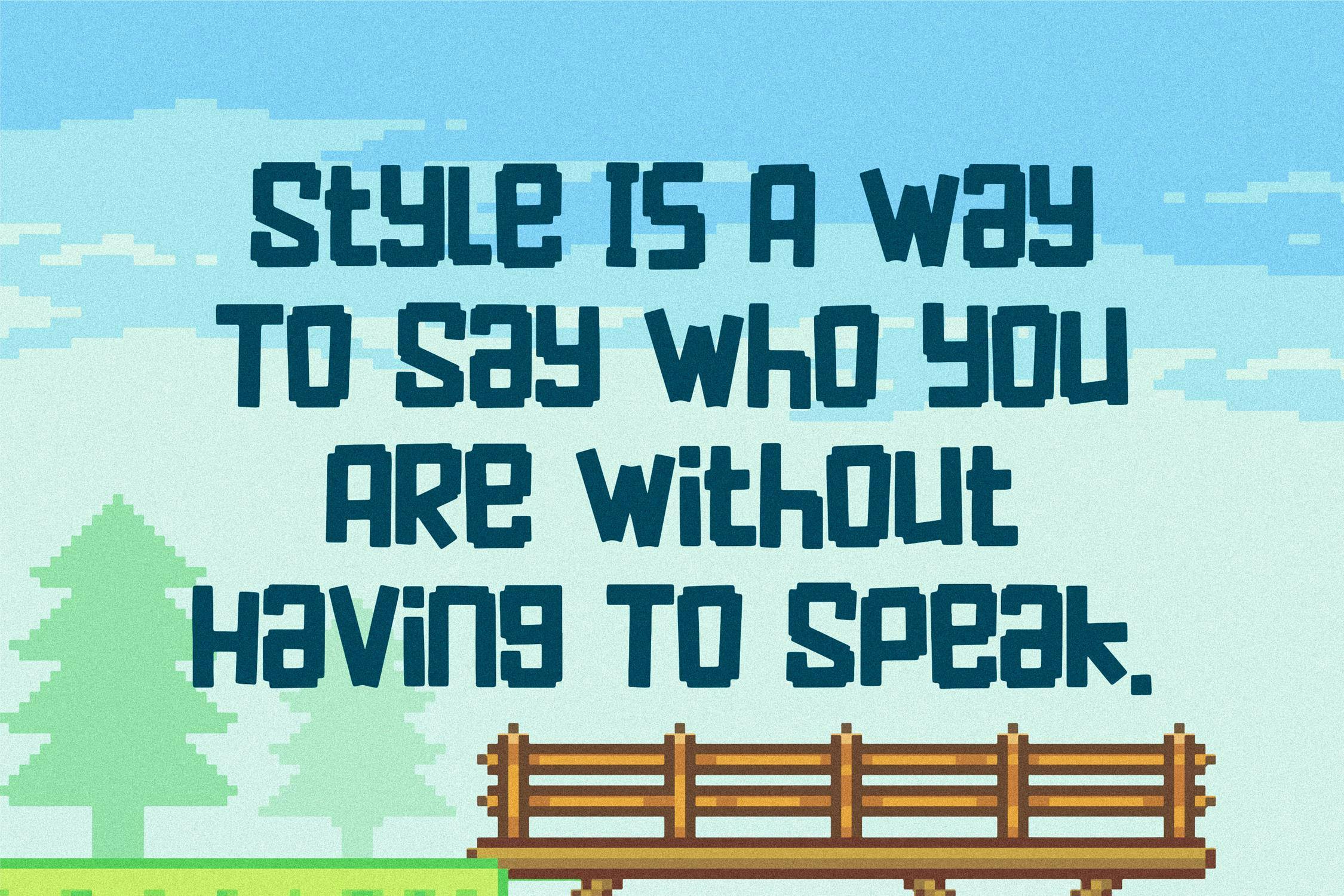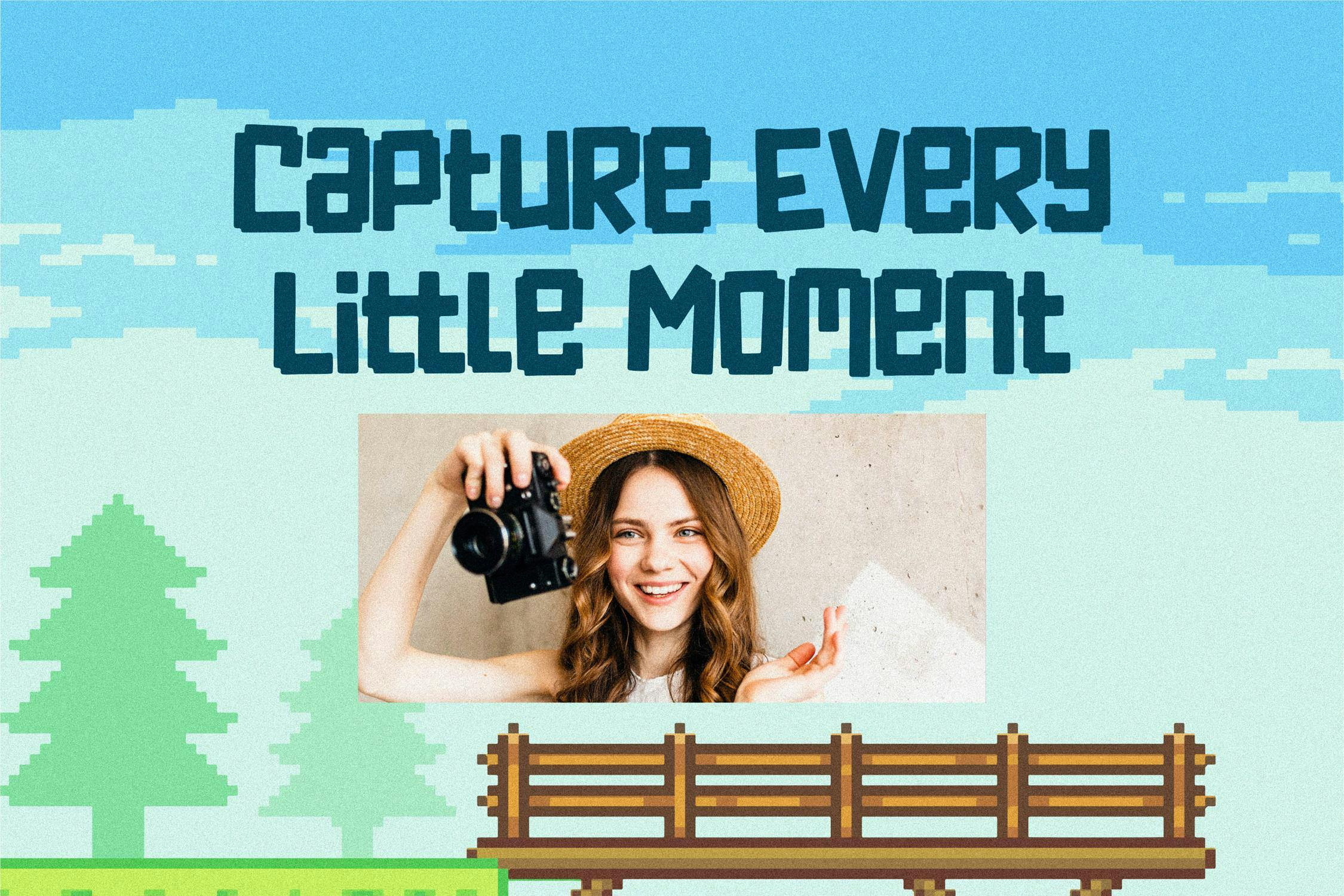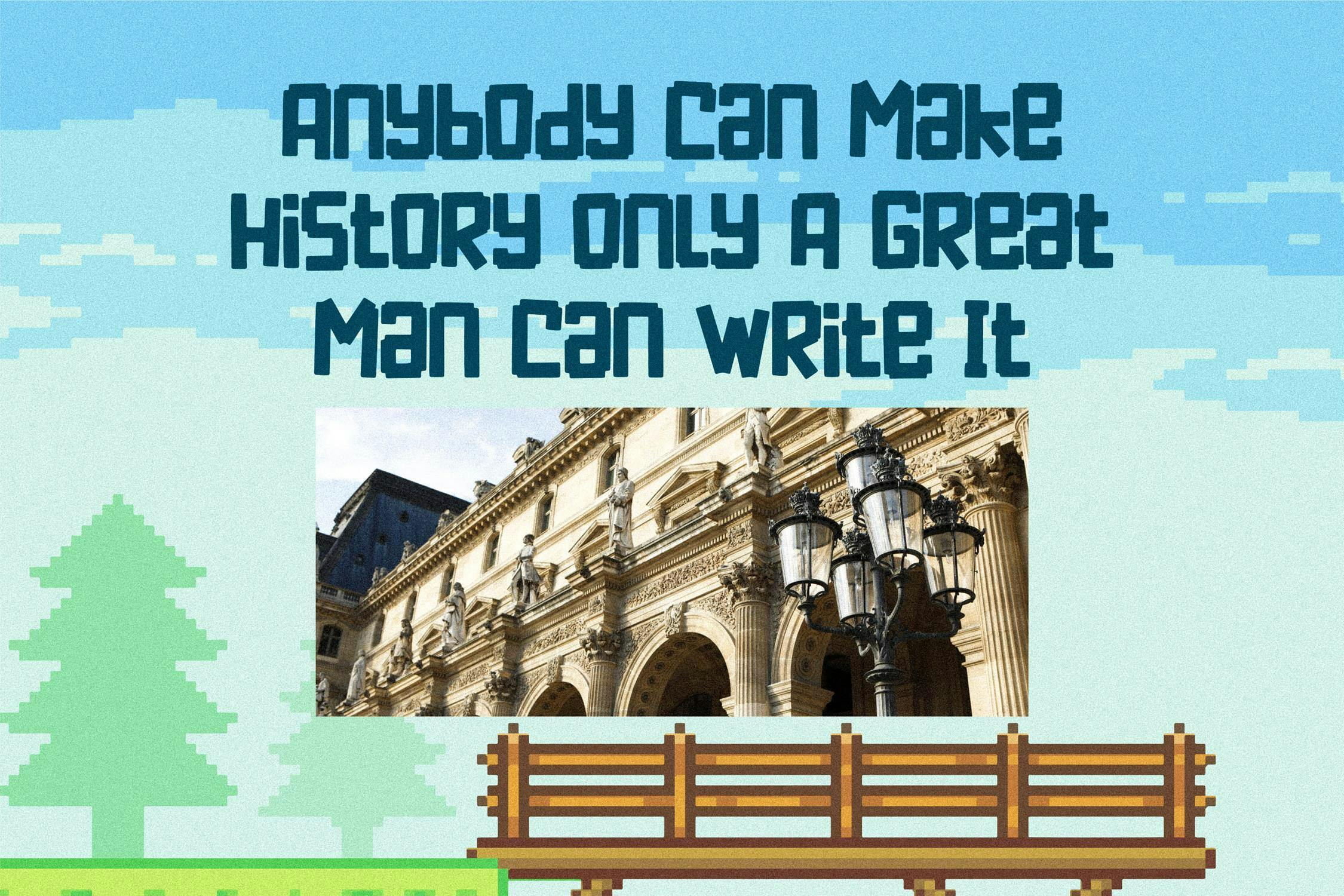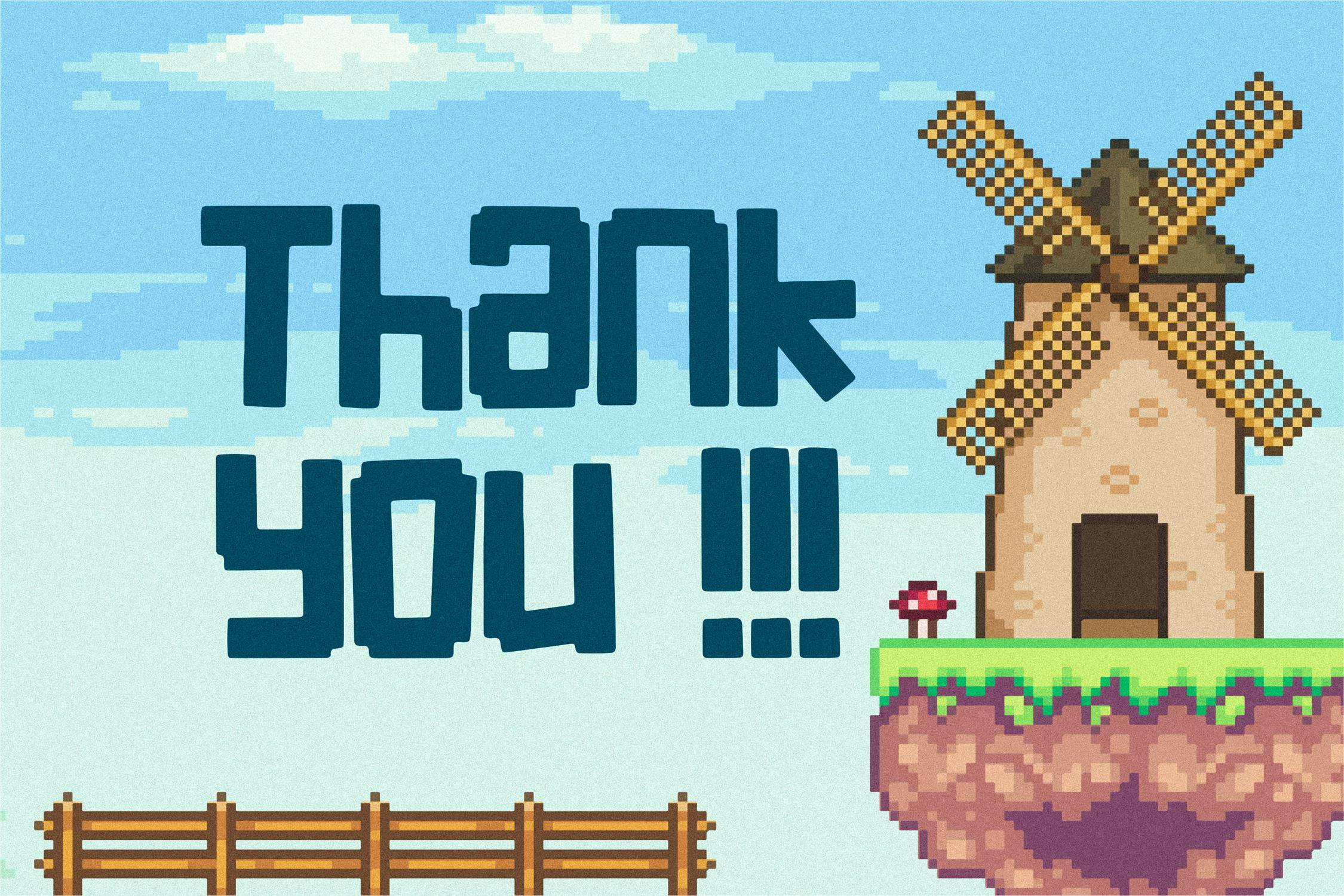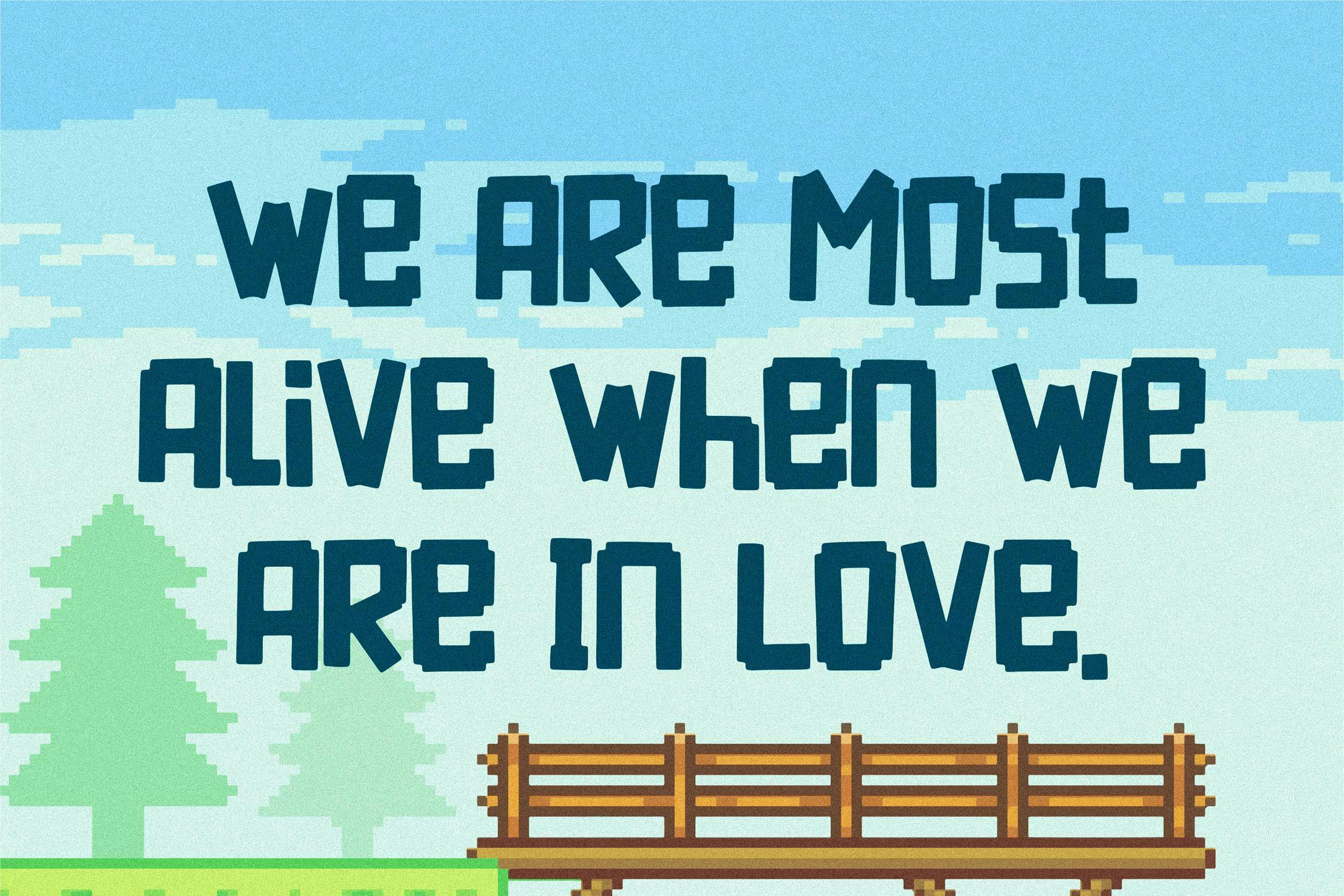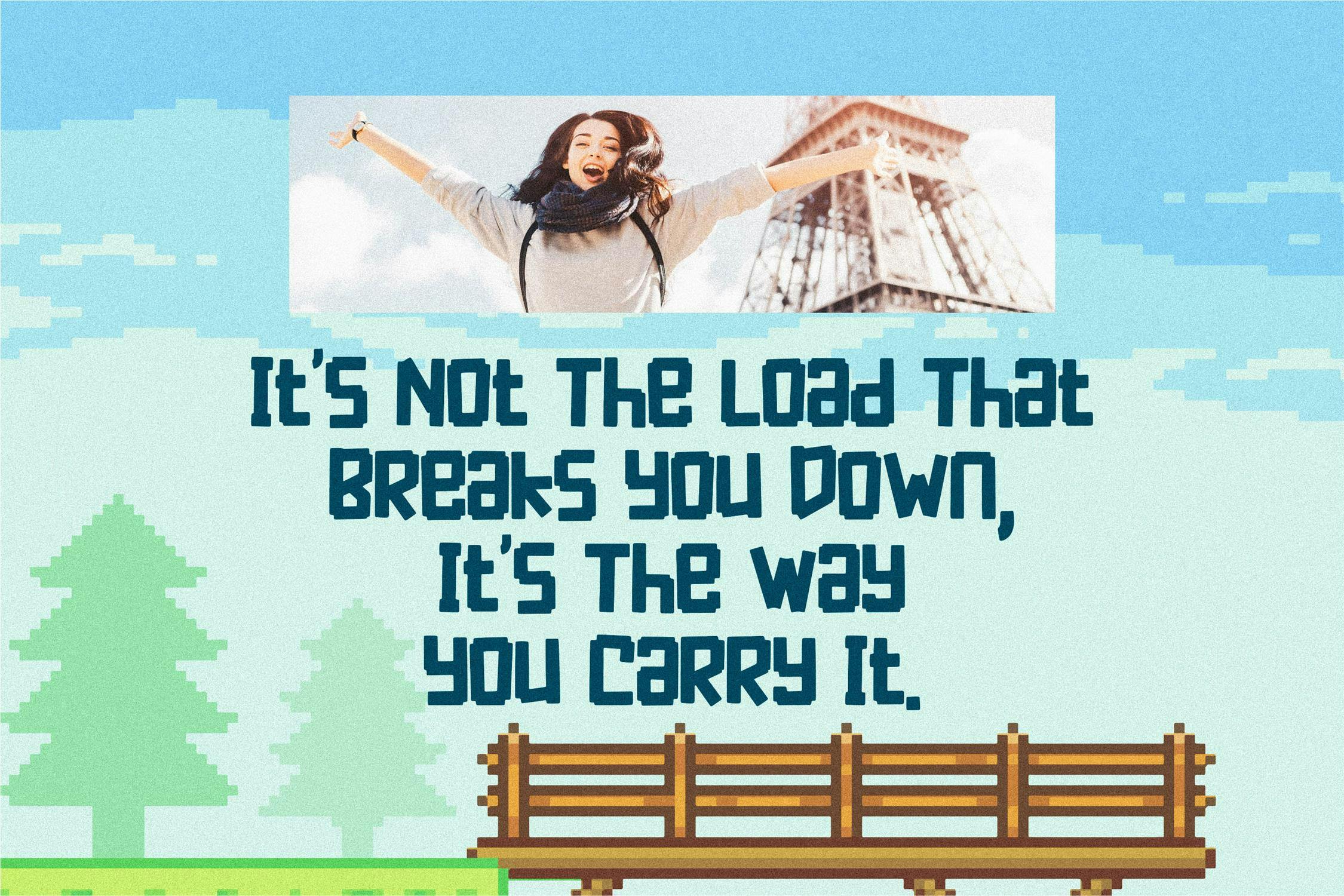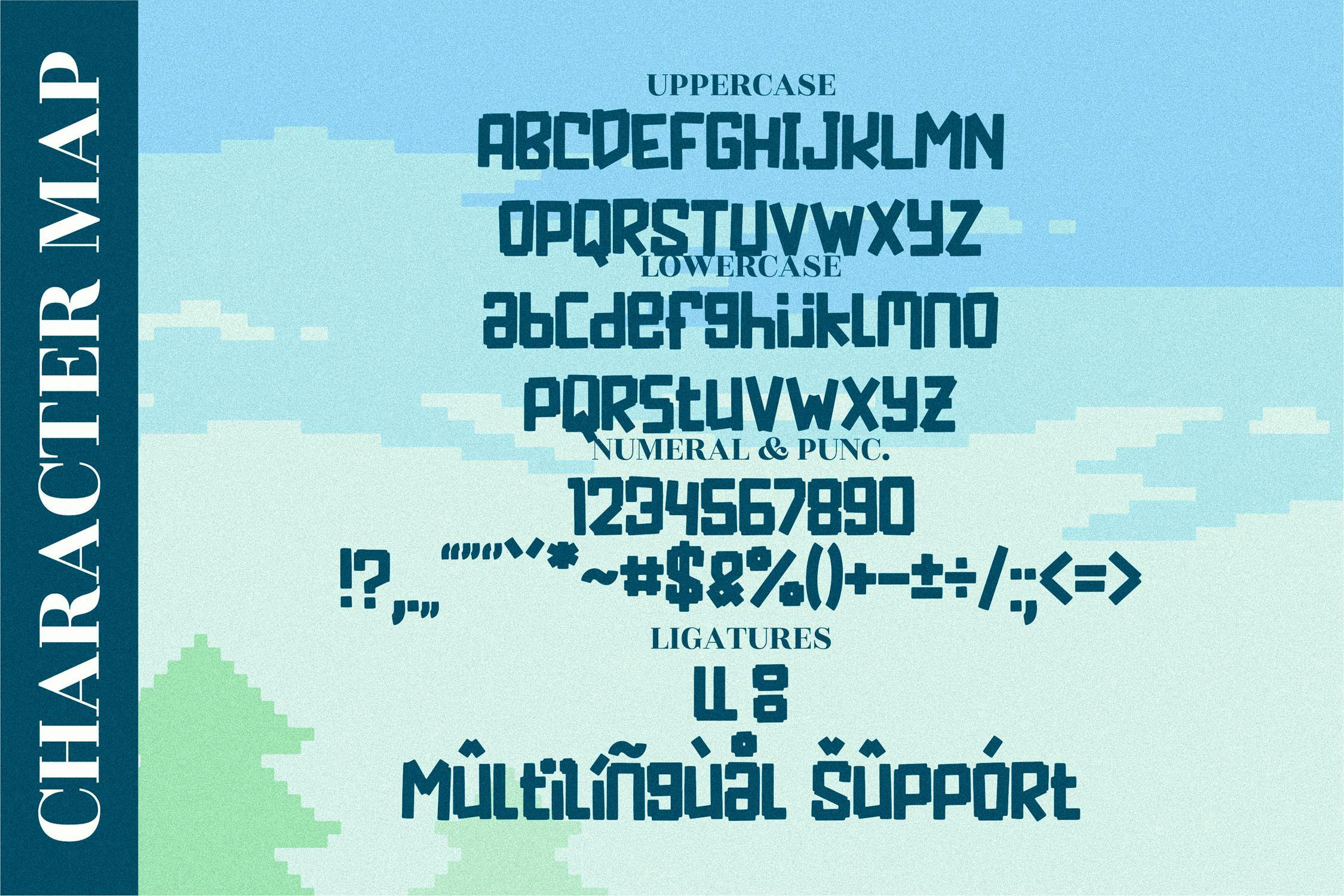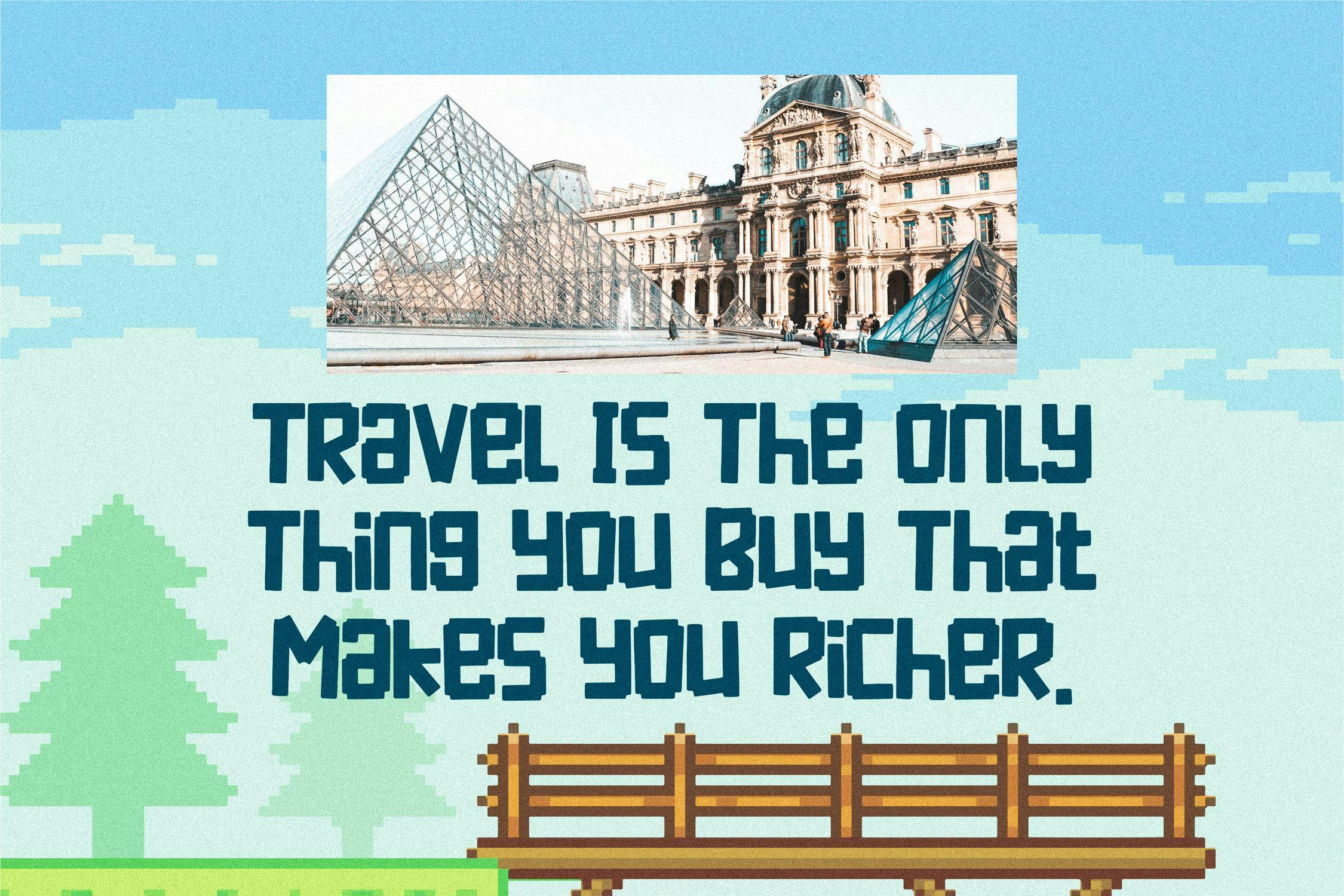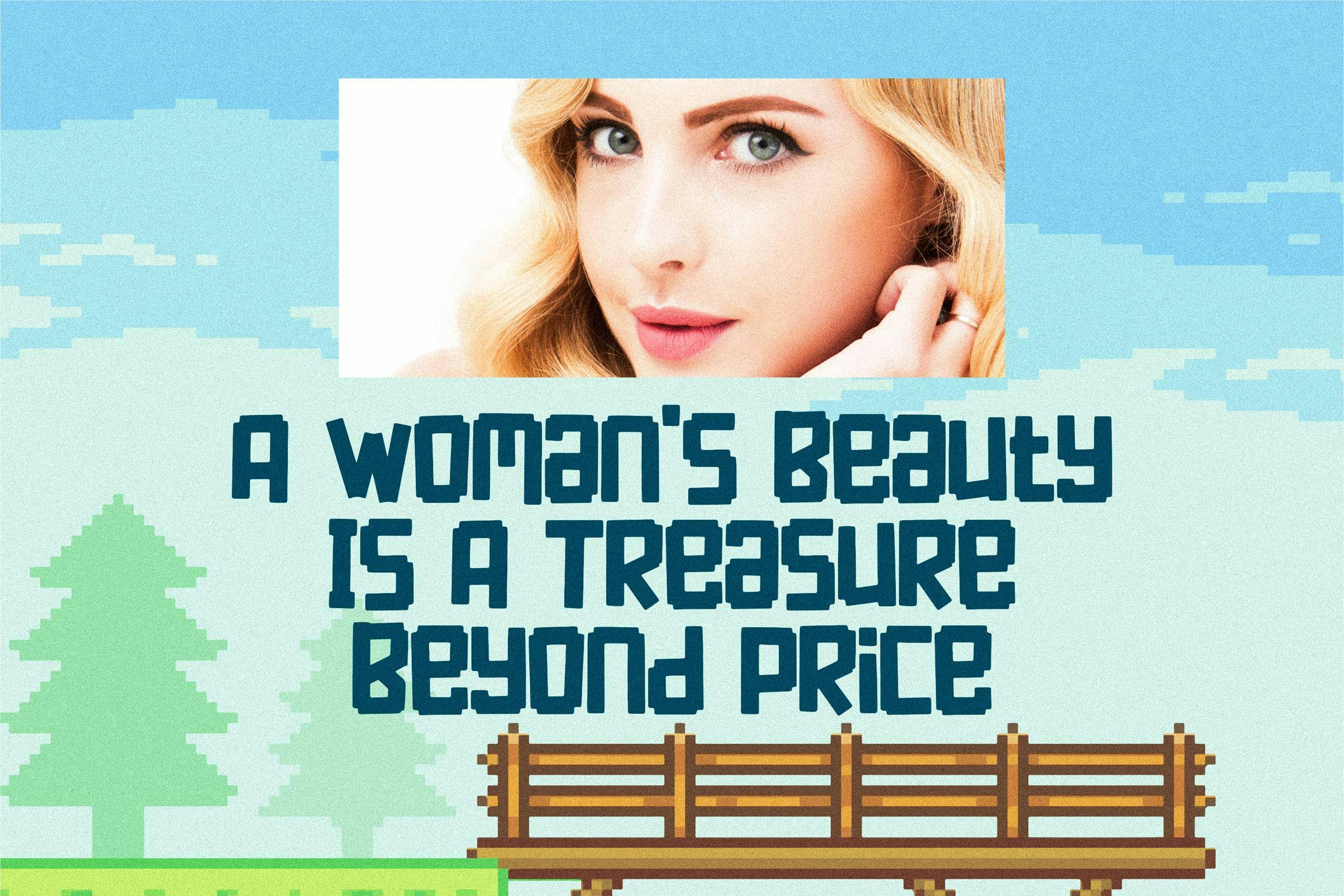
Pixel Craft Display Font
با دانلود فونت Pixel Craft Display، پروژه‌های خود را به شکلی خلاقانه طراحی کنید.
این فونت برای طراحی پوسترها، پست‌های رسانه‌های اجتماعی، برندینگ، پروژه‌های شخصی و غیره ایده‌آل است.